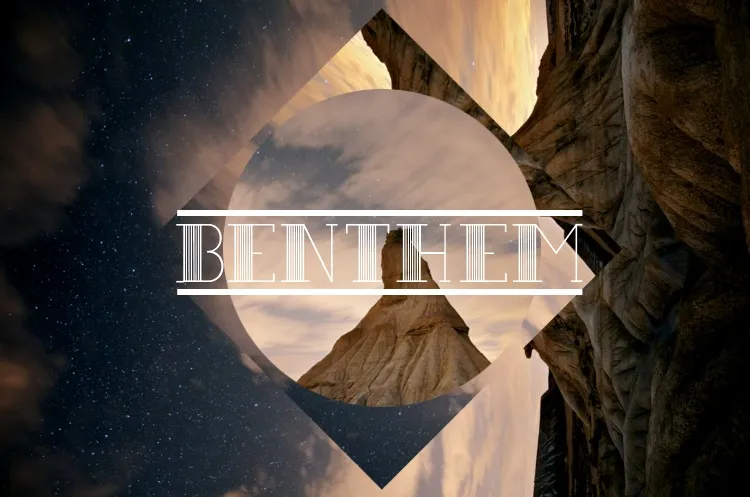
Benthem Font
Esta fonte tipo Benthem foi projetada para destacar visivelmente qualquer projeto que você esteja trabalhando. Suas letras abertas e sem serif dão a ela um apelo forte, tornando-a ideal para layouts de revistas, materiais publicitários, logos ou como cabeçalhos em sua próxima proposta. Seus traços finos e pontas planas da serif garantem um aspecto unificado que permite facilmente combinar múltiplas fontes sem perder o seu brilho distinto. Seja qual projeto você esteja escolhendo para ilustrar, essa fonte é perfeita para adicioná-lo a qualquer design com uma aparente simplicidade mas um tom audacioso e marcante.